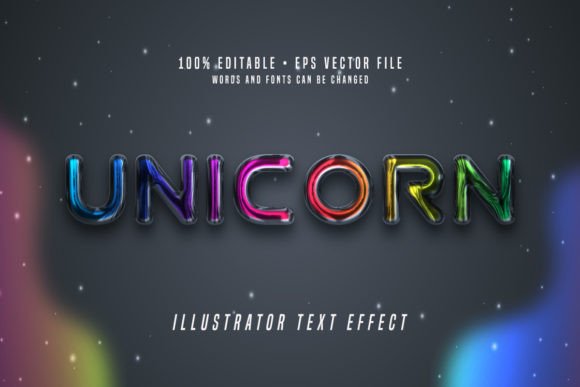
Unicorn 3D Illustrator Text Effect Font
Если вы ищете высококачественные ресурсы, такие как Unicorn 3D Illustrator Text Effect Font, этот премиум-пакет — фантастический выбор для ваших творческих проектов.
Создаете ли вы продукты POD (печать по требованию), свадебные приглашения или графику для социальных сетей, Unicorn 3D Illustrator Text Effect Font станет идеальным выбором.